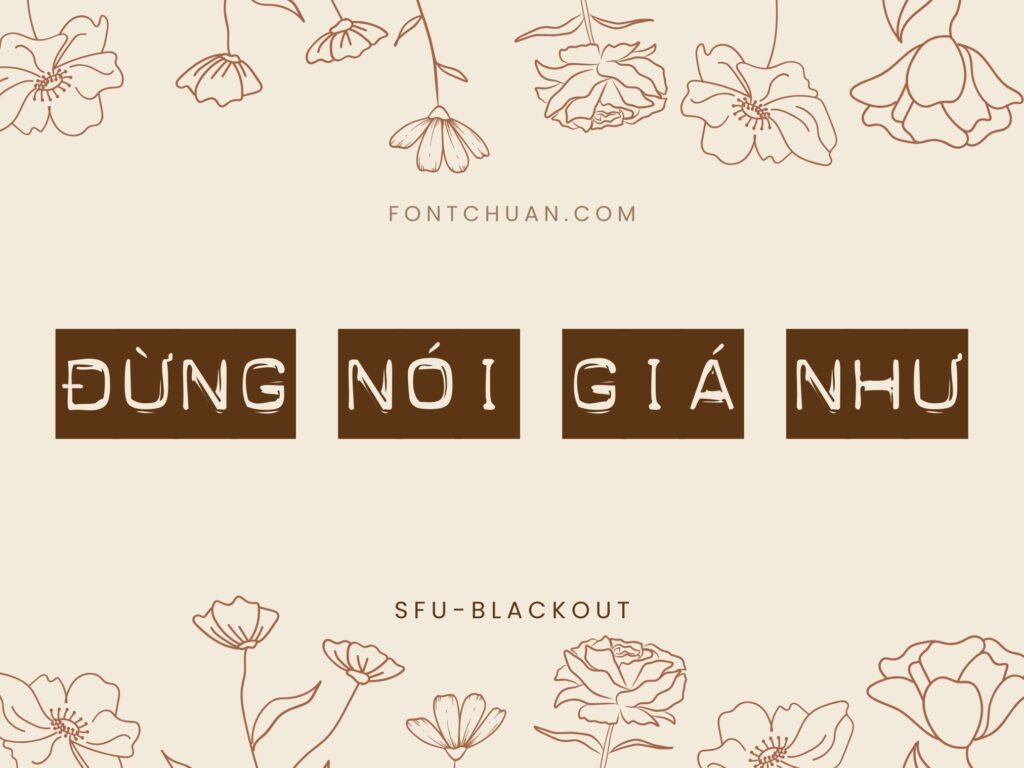
Font Blackout là một kiểu chữ sans-serif đậm, được thiết kế để tạo sự nổi bật và thu hút sự chú ý. Với các nét chữ dày và mạnh mẽ, font này thường được sử dụng trong các tiêu đề, áp phích và thiết kế cần sự nhấn mạnh. Blackout mang lại cảm giác hiện đại và năng động, phù hợp cho nhiều mục đích thiết kế khác nhau
Phiên bản này đã được Việt hóa, hỗ trợ đầy đủ tiếng Việt cùng nhiều ngôn ngữ khác, giúp người dùng dễ dàng ứng dụng trong các dự án đa ngôn ngữ. Font Blackout được sưu tầm và đăng tải bởi thành viên của Font Chuẩn, nhằm mang đến sự lựa chọn đa dạng cho cộng đồng thiết kế
Về đặc điểm thiết kế, Blackout có các nét chữ đậm và liền mạch, tạo cảm giác chắc chắn và mạnh mẽ. Kiểu chữ này rất phù hợp để sử dụng trong các thiết kế như tiêu đề, banner quảng cáo, poster và các ấn phẩm truyền thông cần sự nổi bật
Font Blackout được ứng dụng rộng rãi trong các sự kiện như lễ hội, Halloween, Giáng sinh, Tết, Trung thu. Nó phù hợp với nhiều ngành nghề như quảng cáo, công nghệ, bất động sản, giáo dục, ẩm thực